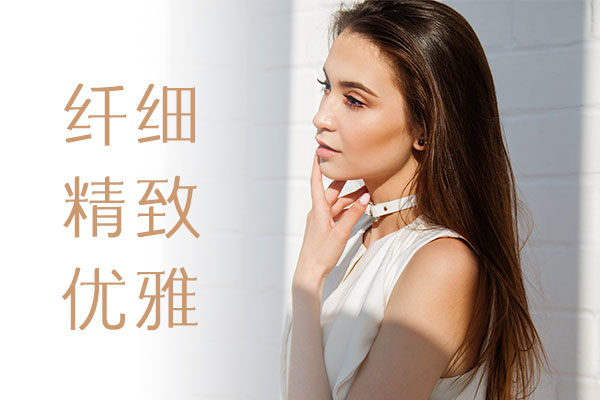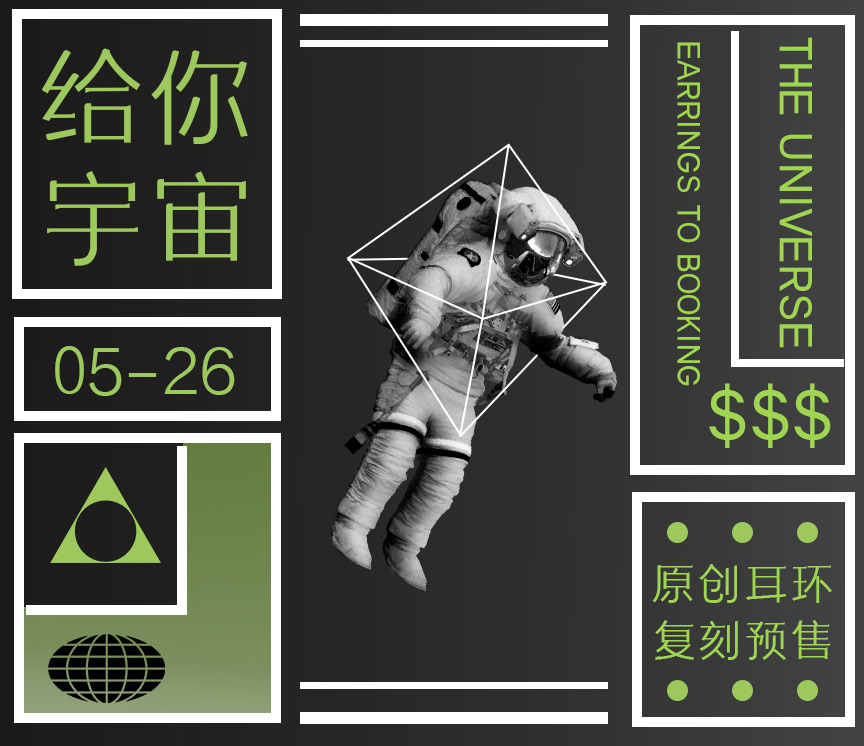
三极素纤简体
三极素纤简体:清新与力量的完美结合
三极字库最近推出了一款备受瞩目的免费商用字体——三极素纤简体。这款字体以其独特的风格和精致的设计,赢得了广大设计师的喜爱。
三极素纤简体的字形设计独具一格,横竖勾带有宋体结构,使得每个字都显得清新自然。同时,这款字体结合了宋体饱满的结构特征和黑体本身的锐利简洁,使得字体既具有精致的外观,又不失力量感。这种设计风格非常适合现代感和科技感的场合,能够为设计师的创意增添更多的可能性。
作为一款免费商用的字体,三极素纤简体覆盖了GB2312规定的6763个汉字,为设计师们提供了全面的选择。无论是在广告设计、产品包装、影视作品还是个人创作中,三极素纤简体都能为作品增添一份高雅和精致的气息。
三极素纤简体效果预览